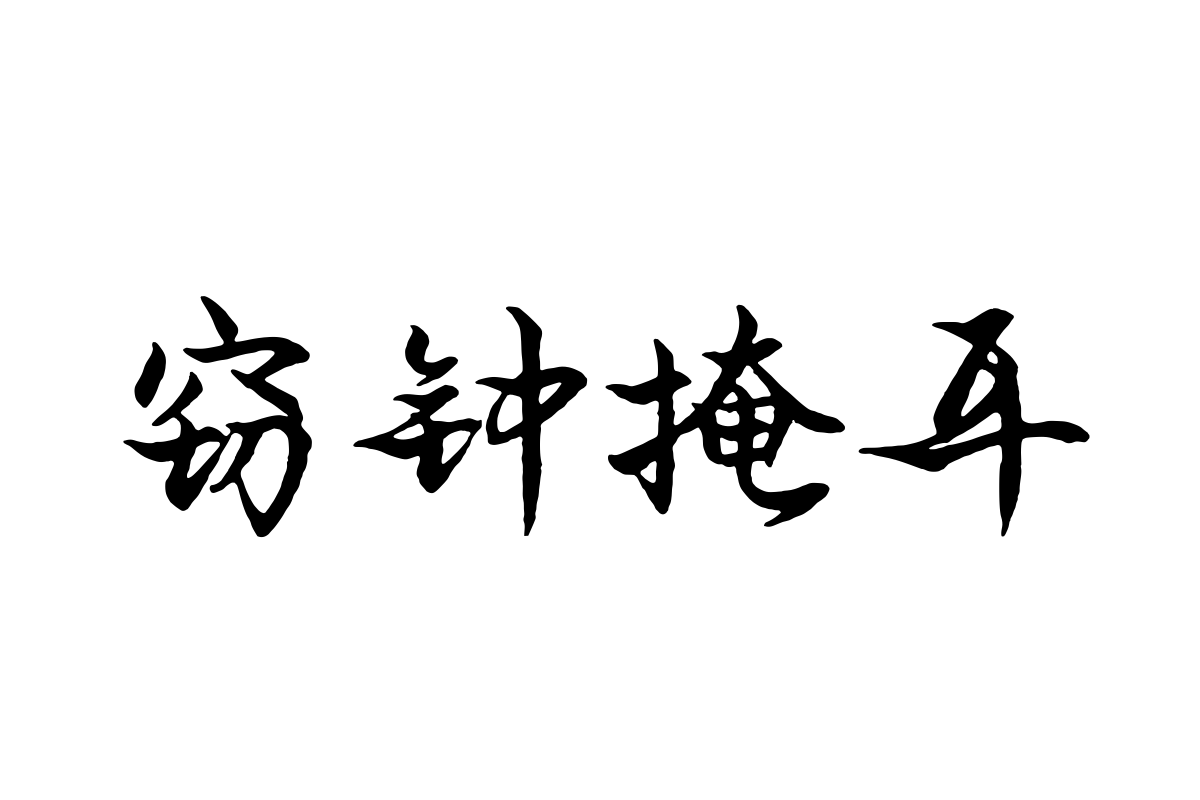
汉仪烟云字体是一款非常独特的中文书法字体。这款字体的设计灵感来源于中国古典诗词中的烟云飘渺之美,给人以宁静、淡雅的感觉。它的字形结构独特,笔画流畅自然,既有古典的韵味,又不失现代感。
汉仪烟云字体适用于各种需要表现中国传统文化和艺术氛围的场合,如设计海报、书籍封面、广告宣传等。无论是商业还是艺术设计,都能为作品增添一份独特的魅力。